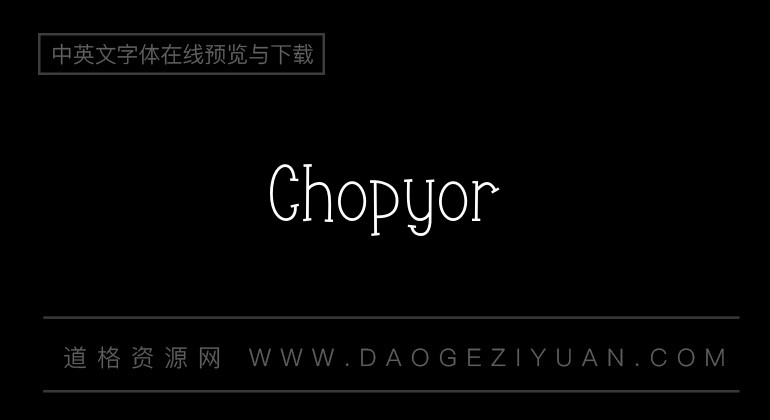
Chopyor 字体是一款新式的字体,它的特点是拥有简洁、清晰的外观,具有良好的可读性,可以在任何场景中使用。它的笔画比较细腻,且有较高的密度,让文字变得更加清晰易读。Chopyor 字体的字体风格属于简约风格,适用于各种类型的文档,可以满足不同的设计需求。内容介绍
Chopyor是一款非常不错的手写艺术字体,具有很好的视觉感,适合于文化类的宣传设计、商业类品牌的广告和产品包装设计以及个性化文字排版等较多场景。